Skład tekstu − krój pisma w składzie tekstu
1. Do składu wybierajmy jak najmniejszą ilość krojów pisma.
2. Jeden lub dwa kroje pisma doskonale spełnią swoje zadanie w składzie każdego rodzaju publikacji.
3. Najlepiej wybrać jeden bardzo bogaty krój, który posiada funkcje OpenType.
4. Jeśli chcemy użyć dwóch krojów pisma muszą być one wyraźnie od siebie różne, niezależnie od tego jak długi ma być projekt.
5. Kroje pisma, które prezentują różną szerokość liter nie współgrają dobrze w jednym dziele.
6. Nie łączmy ze sobą w jednym akapicie krojów o różnej szerokości liter. Jeśli chcemy użyć wąskiego kroju, to użyjmy go oddzielnie od liter regularnych. Można wykorzystać taki krój do sformatowania nagłówków, podpisów do zdjęć, czy do wyróżnienia. Taka sama reguła dotyczy pism szerokich.
7. Gdy chcemy dobrać idealny krój pisma do składu długiego tekstu warto zmierzyć następujące odległości:
→ wewnętrzne i zewnętrzne światło każdego znaku jest w miarę równe, tzn. przestrzeń wewnętrzna litery „O” musi być w przybliżeniu równa przestrzeni między tą literą a literą następną:
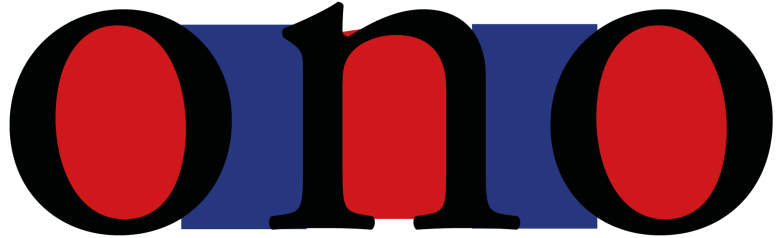
Krój pisma Adobe Garamond Pro